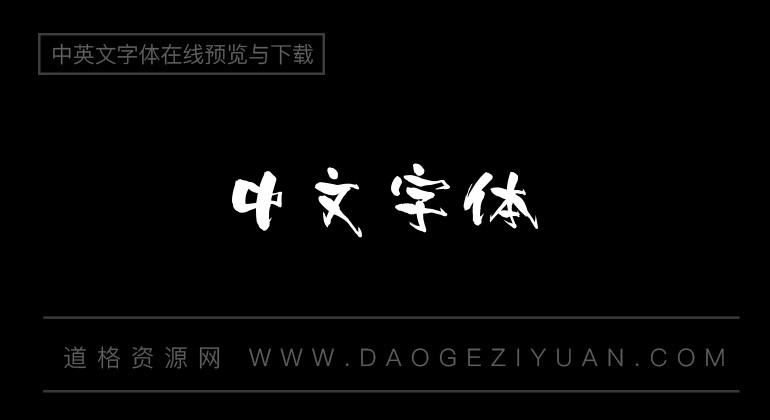
潮字社杨肖清书繁
潮字社杨肖清书繁字体是一款中国传统书法风格的字体,由潮字社设计师杨肖清设计。它以清秀的笔画和传统的书法结构为基础,以简约的线条表现出精致的书法结构,体现出传统的中国书法风格。该字体的笔画柔和,细节精致,结构严谨,能够很好地表达出书法的精髓,是一款非常经典的字体。
潮字社杨肖清书繁是一款非常不错的手写艺术字体,具有很好的视觉感,适合于文化类的宣传设计、商业类品牌的广告和产品包装设计以及个性化文字排版等较多场景。